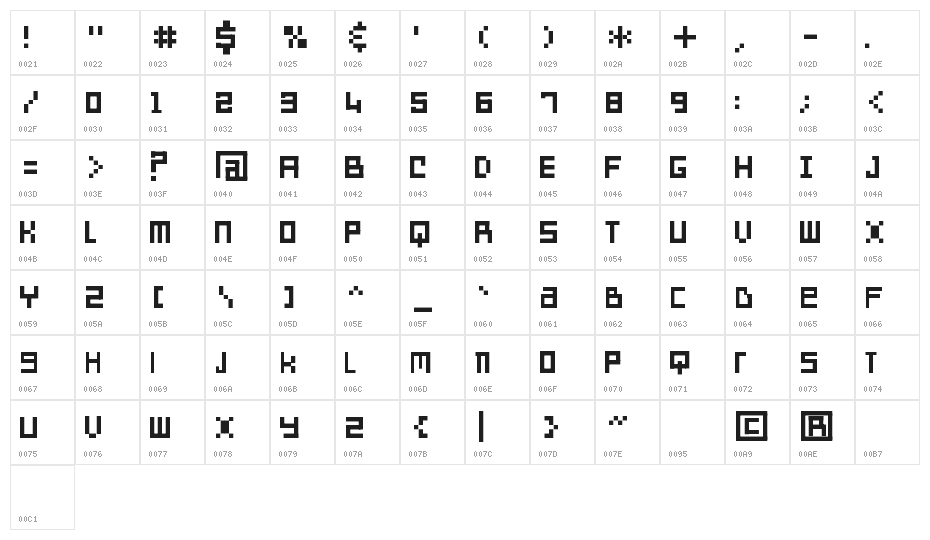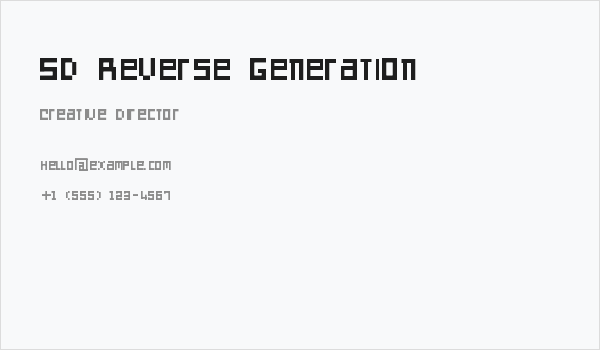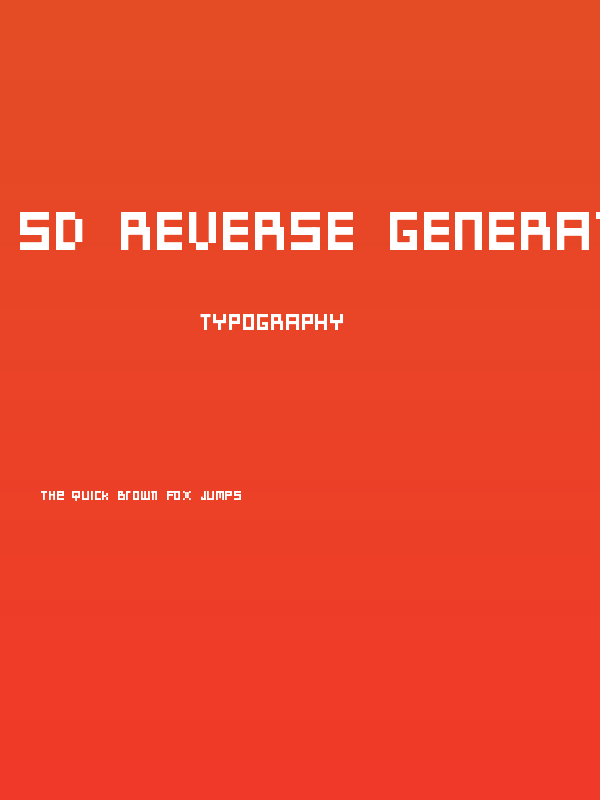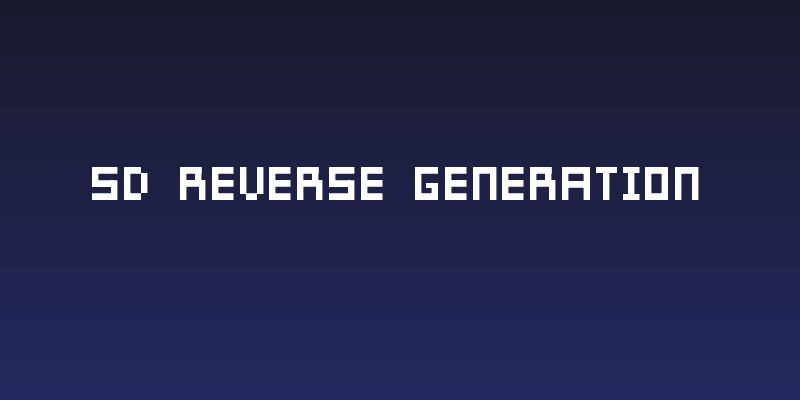
SD Reverse Generation Font
| समग्र शैली | Retro, Digital |
| उपयोग का मामला | Headlines, Logos, Digital Art |
| सुझाए गए प्रोजेक्ट | Ideal for video game graphics, tech-themed posters, retro designs, and digital art projects. |